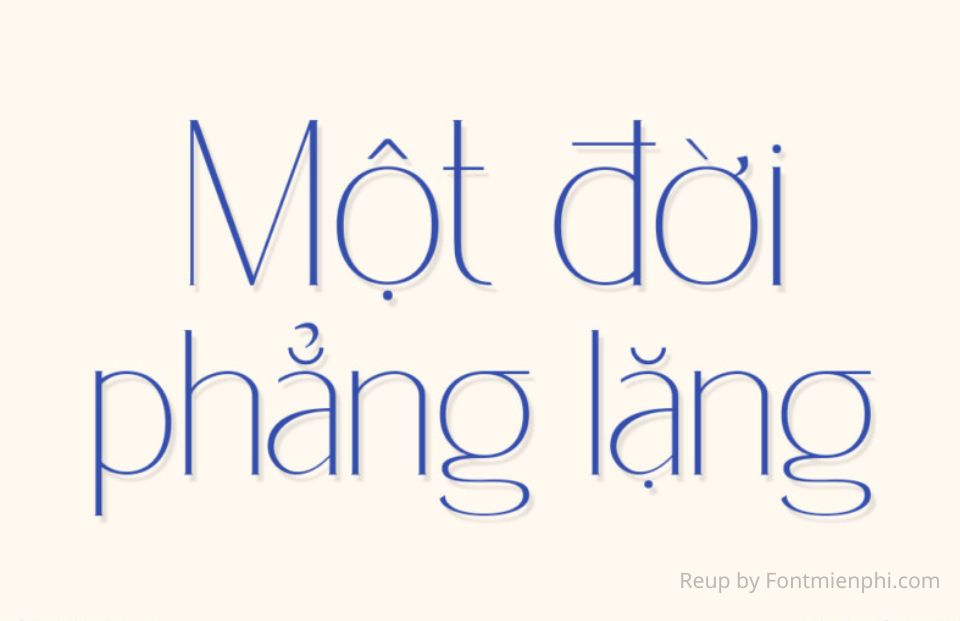
Bạn đang tìm kiếm một phông chữ toát lên vẻ đẹp quý phái, thanh lịch nhưng vẫn đảm bảo hiển thị tiếng Việt trọn vẹn không bị lỗi dấu? Font Việt hóa 1FTV VIP Delicate Elegance chính là giải pháp tối ưu dành cho bạn. Được nâng cấp và Việt hóa tỉ mỉ, bộ font này là “vũ khí bí mật” giúp các dự án thiết kế của bạn nâng tầm đẳng cấp ngay lập tức.
1. Font 1FTV VIP Delicate Elegance Là Gì?
1FTV VIP Delicate Elegance là một typeface thuộc dòng serif (có chân) hoặc script (tùy biến) mang hơi hướng hiện đại pha lẫn cổ điển. Đúng như tên gọi “Delicate Elegance”, font chữ này tập trung vào sự tinh tế, những đường nét thanh mảnh, mượt mà và tỉ lệ chữ cân đối.
2. Những Ưu Điểm Nổi Bật Của 1FTV VIP Delicate Elegance
Việt Hóa Chuẩn Xác 100%: Dấu câu tiếng Việt được thiết kế thủ công, căn chỉnh tỉ mỉ để hòa hợp tuyệt đối với phom dáng của các chữ cái gốc, không gây cảm giác gượng gạo hay rời rạc.
Thiết Kế Tinh Tế, Độc Quyền (VIP): Sở hữu những nét thanh nét đậm (contrast) rõ ràng, tạo cảm giác sang trọng, đắt tiền và bắt mắt.
Ký Tự Thay Thế Đa Dạng (Alternates & Ligatures): Cung cấp nhiều bộ ký tự thay thế uốn lượn nghệ thuật, giúp bạn tự do sáng tạo typography mang đậm dấu ấn cá nhân.
3. Ứng Dụng Hoàn Hảo Trong Mọi Dự Án Thiết Kế
Với sự thanh lịch vượt thời gian, Font Việt hóa 1FTV VIP Delicate Elegance là lựa chọn hàng đầu cho các ấn phẩm mang tính cao cấp:
Nhận diện thương hiệu (Branding): Rất phù hợp để làm logo hoặc font chữ chủ đạo cho các ngành hàng thời trang cao cấp, mỹ phẩm, spa, trang sức hoặc bất động sản nghỉ dưỡng.
Thiết kế thiệp cưới (Wedding Invitations): Mang lại sự lãng mạn, bay bổng và trang trọng cho những tấm thiệp cưới, thiệp mời sự kiện VIP.
Bao bì sản phẩm (Packaging): Giúp nâng tầm giá trị sản phẩm trên các thiết kế vỏ hộp, nhãn mác nước hoa, rượu vang…
Tạp chí & Nhiếp ảnh: Phù hợp làm tiêu đề (Headline) cho các trang bìa tạp chí, lookbook thời trang hoặc chèn typography vào ảnh nghệ thuật (Quote typography).